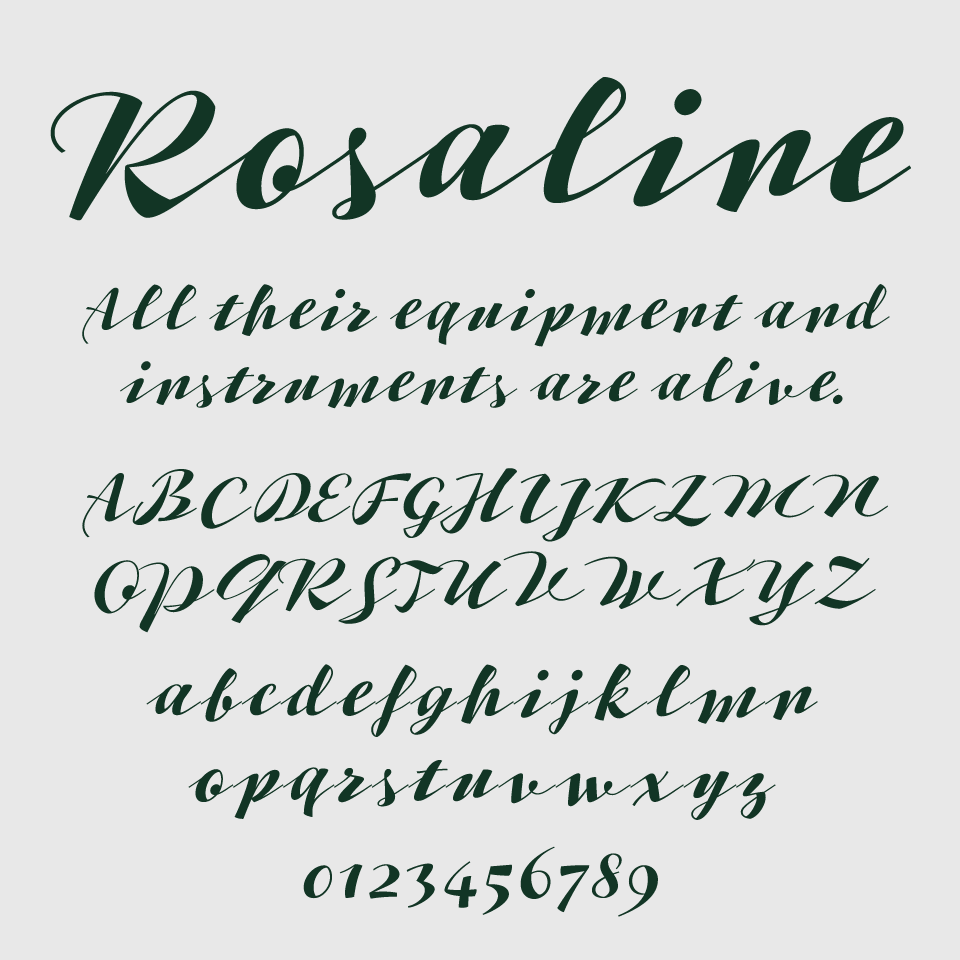
Rosalineフォントは、柔らかな流線と筆のかすれを思わせるタッチが、優雅で洗練された印象なカリグラフィー風フォントです。
カリグラフィーの要素をベースにしながらも、モダンなバランス感で整理されていて、クラシックすぎない華やかさがあります。
ラグジュアリーな雰囲気のブランドロゴや結婚式のメッセージ、手紙・カード類にも似合う上品なフォントです。繊細で流れるような筆致が、ロマンチックなムードをそっと添えてくれるフォントです。